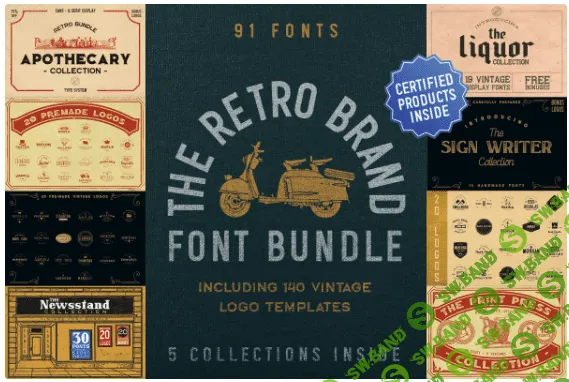
Название: The Retro Brand Font Bundle (2019)
Набор шрифтов ретро-бренда
Этот пакет включает в себя все 5 коллекций моих шрифтов, которые я когда-либо создавал, + 50 уникальных шаблонов логотипов на основе этих шрифтов. В комплекте шрифтов Retro Brand Font Bundle есть большой выбор различных стилей шрифтов, вы обязательно найдете то, что вам нужно. Этот пакет идеально подходит для винтажного брендинга и других проектов в стиле ретро!